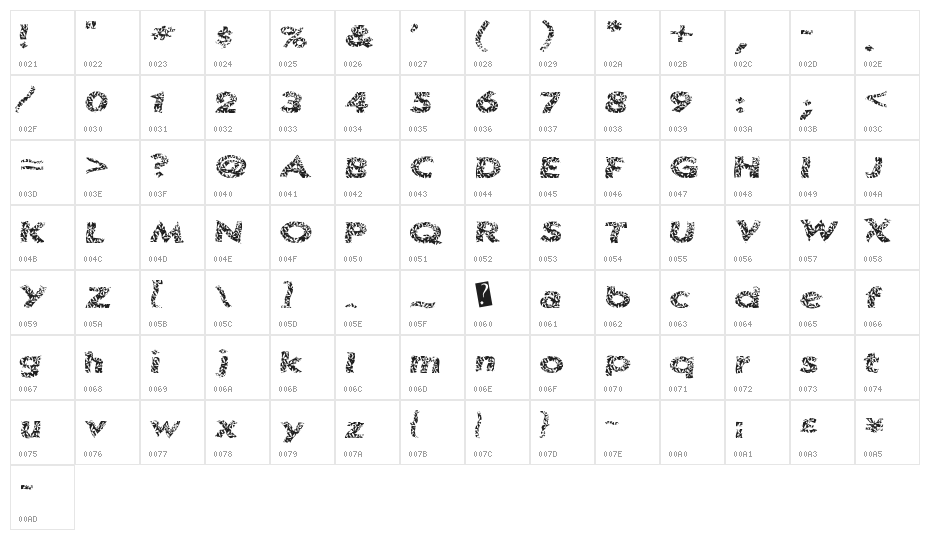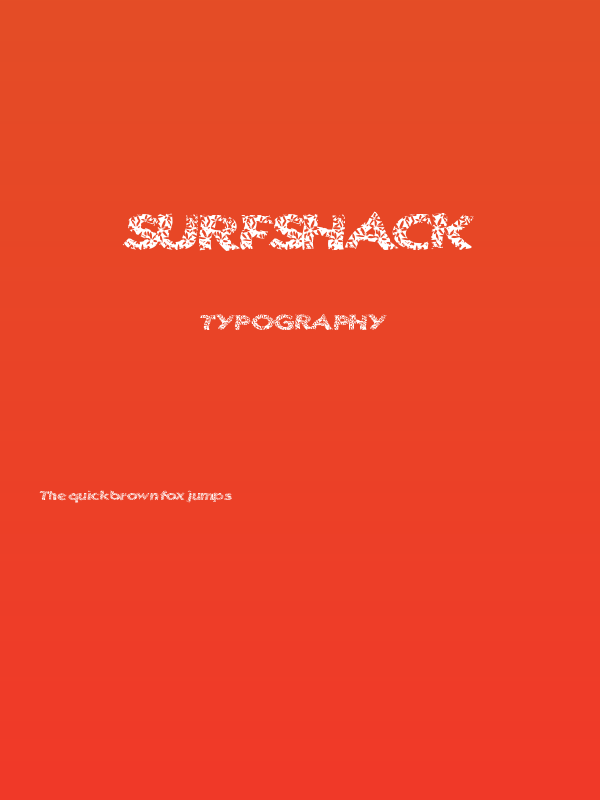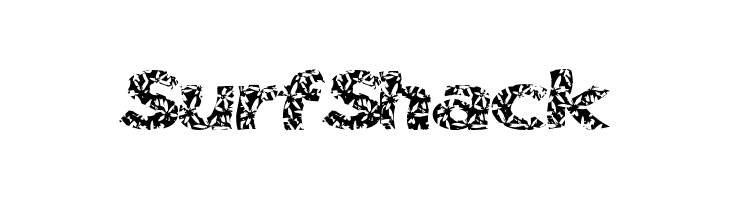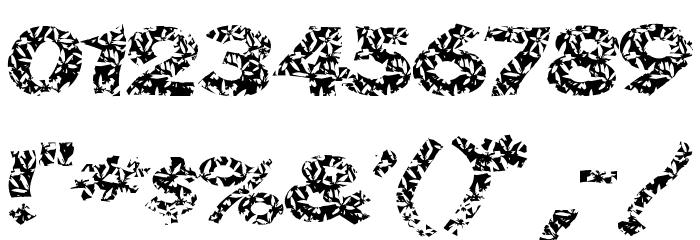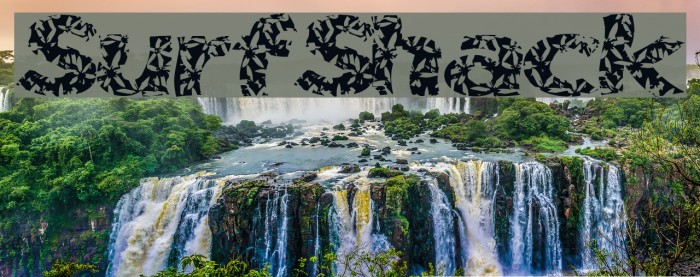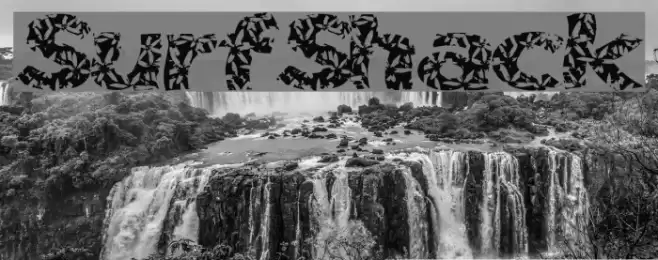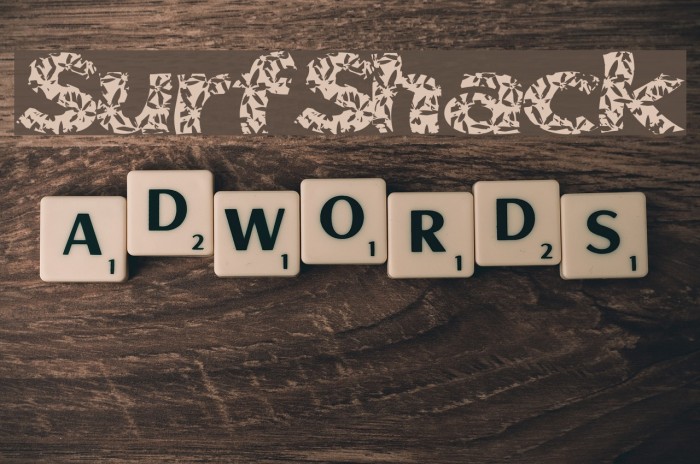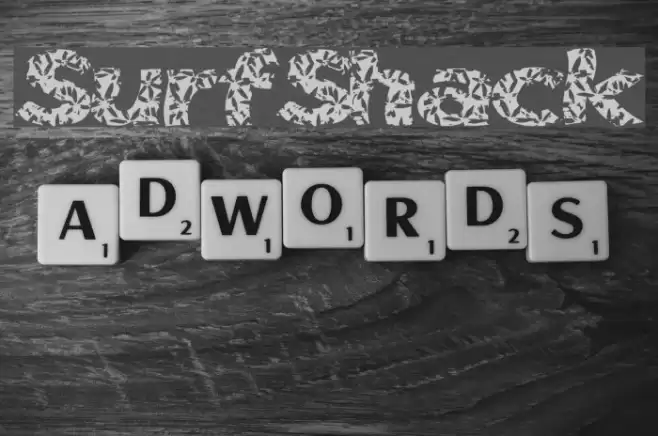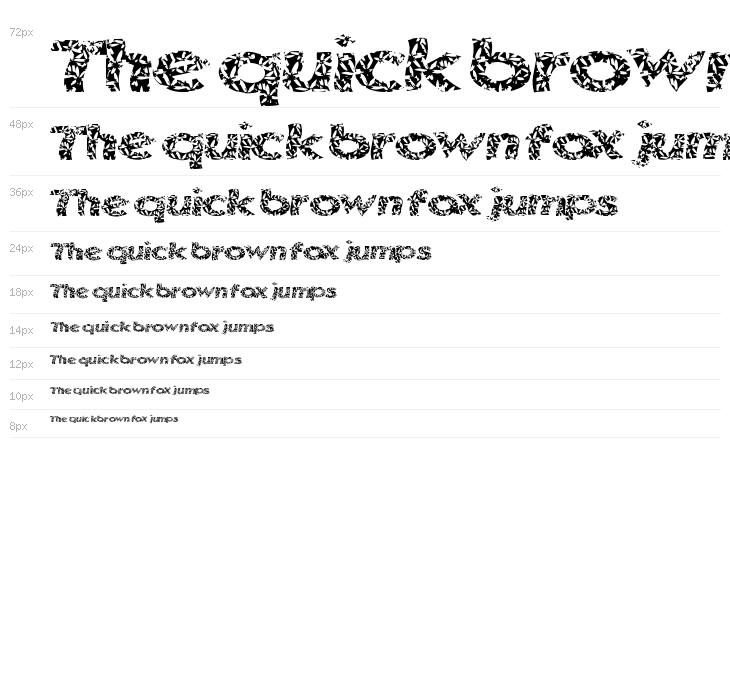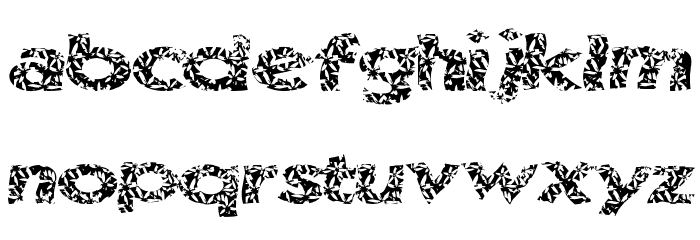
SurfShack Font
| Caso de uso | Logos, Posters, Headlines |
| Proyectos propuestos | Ideal for beach-themed posters, surf shop branding, event flyers, and creative design projects that require a bold, decorative touch. |